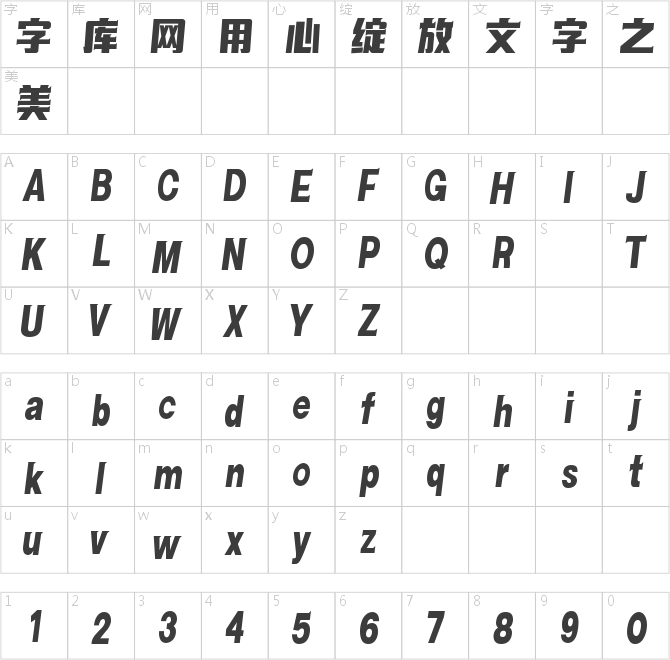
字魂悅動(dòng)音速黑 詳情頁(yè)
字體名稱(chēng): 字魂悅動(dòng)音速黑
字魂悅動(dòng)音速黑字體字庫(kù)是一款讓人賞心悅目、百看不厭的中文字體,適合各類(lèi)廣告和產(chǎn)品包裝設(shè)計(jì)應(yīng)用,字體大小1.63MB,格式為ttf字體,上傳用戶是曾紹文,作者/版權(quán)方為字魂